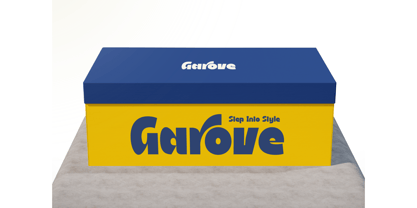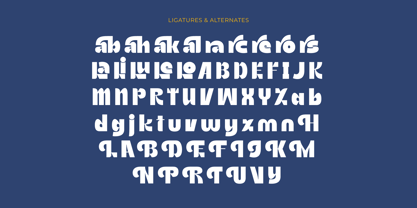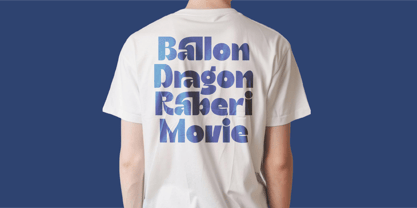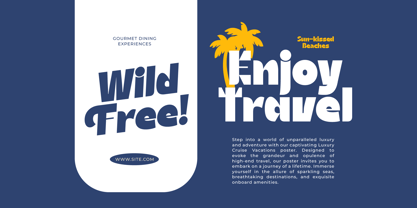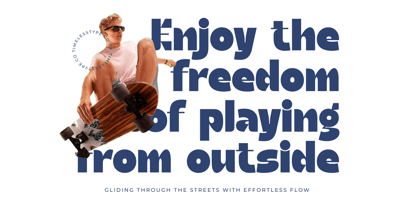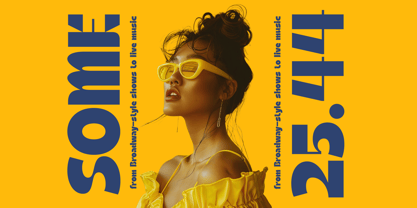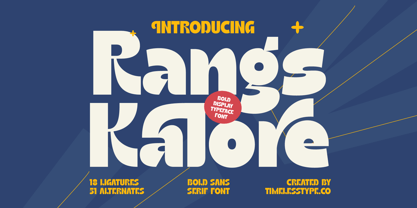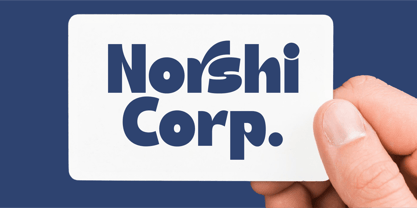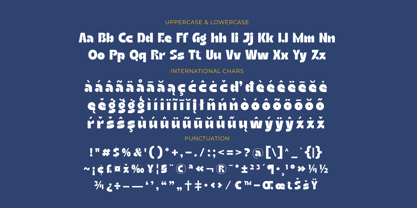
Rangs Kalore
por Timelesstype Studio
La familia tipográfica Rangs Kalore fue diseñada por Heru Utama Putra y publicada por Timelesstype Studio. Rangs Kalore contiene 2 estilos y opciones de paquete familiar.
Rangs Kalore - Bold Sans Serif Font , from Timelesstype, Suitable for any projects such as: logos, branding projects, homeware designs, product packaging, mugs, quotes, posters, shopping bags, t-shirts, book covers, name card, invitation cards, greeting cards, label, photography, watermark, special events, and all your other luxury and beautiful projects that need a Luxury Serif taste.